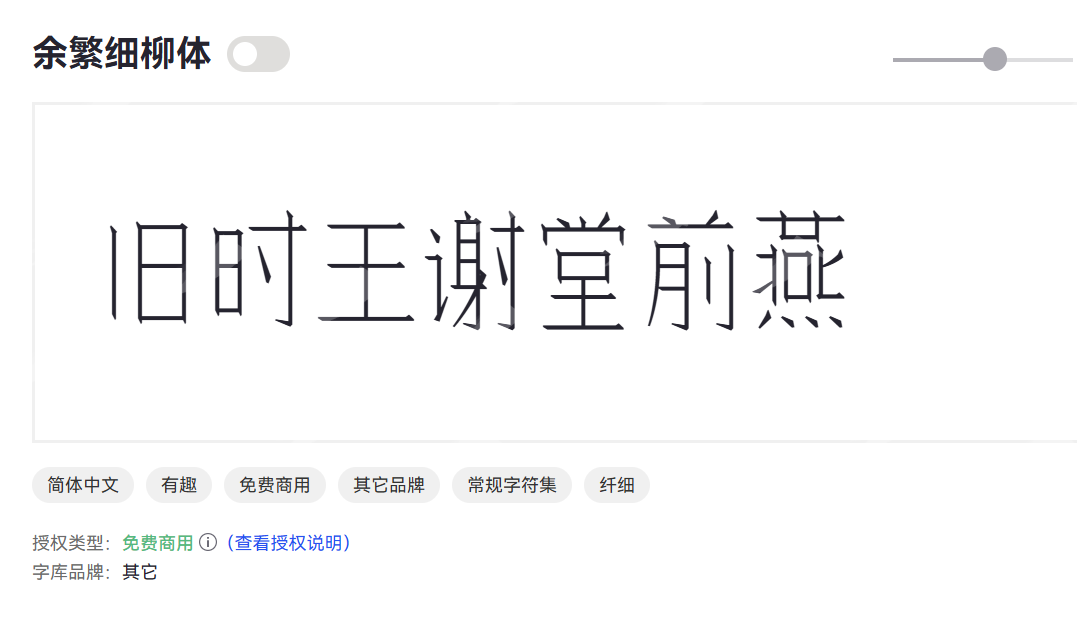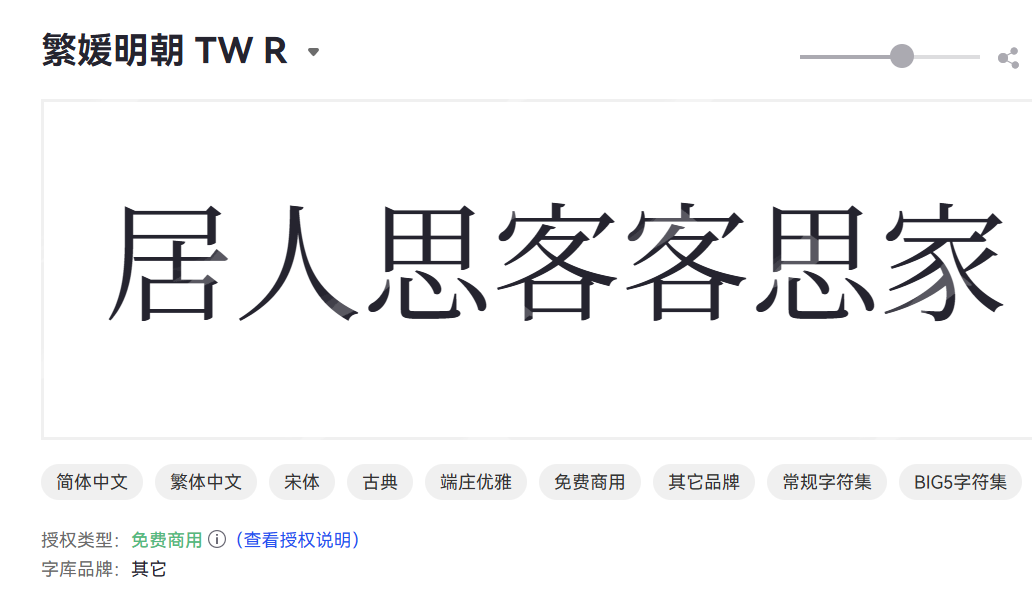
繁体字体可以商用吗?6 款可以免费商用的繁体字体
繁体字体是用来呈现繁体中文的字形集合,与我们常用的简体中文相对,繁体中文保留了汉字最原始、最复杂的笔画结构和字形。
每一个繁体字都像一幅微型的画作,笔画之间相互交织,结构严谨,充满着美学上的平衡感。例如,“龍”字比“龙”字多了许多笔画,但正是这些看似繁复的笔画,构筑了它独特的视觉张力。本文重点给大家分享 7 款可以免费商用的繁体字体。
本文就重点给大家介绍 6 款可以免费商用的繁体字体。
6 款可以免费商用的繁体字体
余繁丹青宋
余繁丹青宋是一款将传统宋体和国风的写意结合的繁体字体。它汲取了中国传统丹青水墨画的精髓,在宋体的骨架上融入了自然流畅、富有韵律感的笔墨细节。
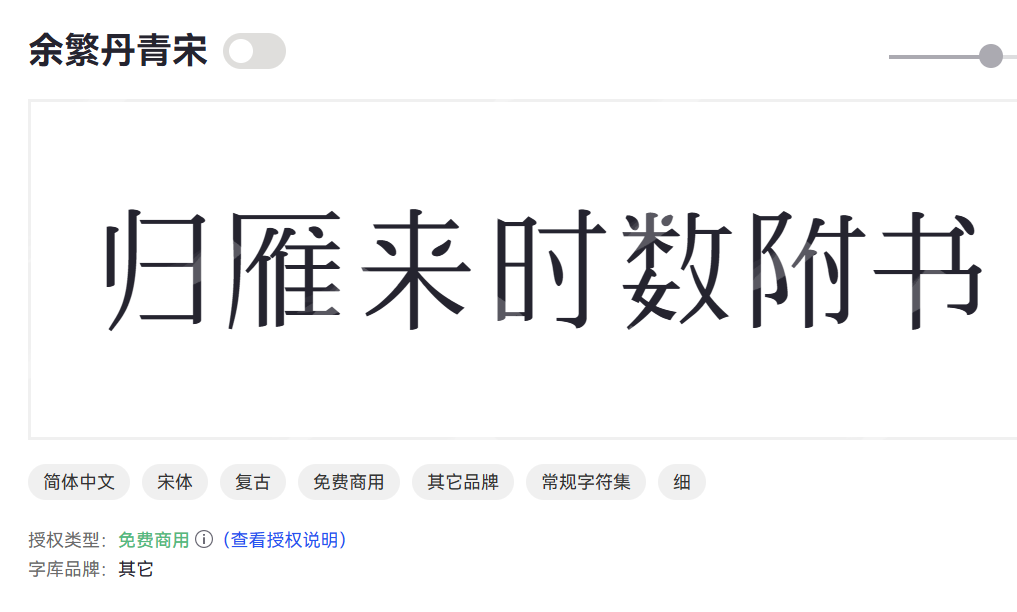
- 继承了宋体横细竖粗、结构严谨的特点,整体风格端庄大气。
- 浓厚的东方美学和传统文化气息。
- 笔画之间的衔接和转折自然流畅,富有节奏感。
- 适用于高端文化产品、艺术展览、国潮品牌、茶道、中式餐饮、文创设计等场景。
余繁细柳体
余繁细柳体是一款以柳条的纤细、柔美、飘逸为设计灵感的艺术字体。
- 整体字形舒展,富有动态美,不拘泥于传统字体的刻板。
- 透露细腻与优雅气质。
- 清新、淡雅、富有诗情画意的氛围。
- 适用于女性品牌与浪漫主题,我记得在一个三八节的海报就用的这款字体、
繁媛明朝
繁媛明朝保留明朝体横细竖粗、字形端正的古典韵味之余,融入了更为精致和女性化的细节,使得字体更加典雅、秀丽。
- 继承了明朝体横细竖粗、笔画棱角分明的经典特征。
- 笔画处理更为考究,细节丰富,展现出雅致的美感。
- 在古典中融入柔和元素,使其更具亲和力。
- 适用于高端文化品牌、复古风格设计、艺术品宣传、国风产品包装、书籍装帧、传统节庆活动等场景。
Aa可爱繁体字
Aa可爱繁体字是一款专为追求萌趣与个性的设计师打造的繁体中文字体。它将繁体字的传统结构与现代的可爱风格相融合,笔画圆润、饱满,字形活泼生动,充满了童真和亲和力,是传递轻松愉快设计场景的不错的选择。
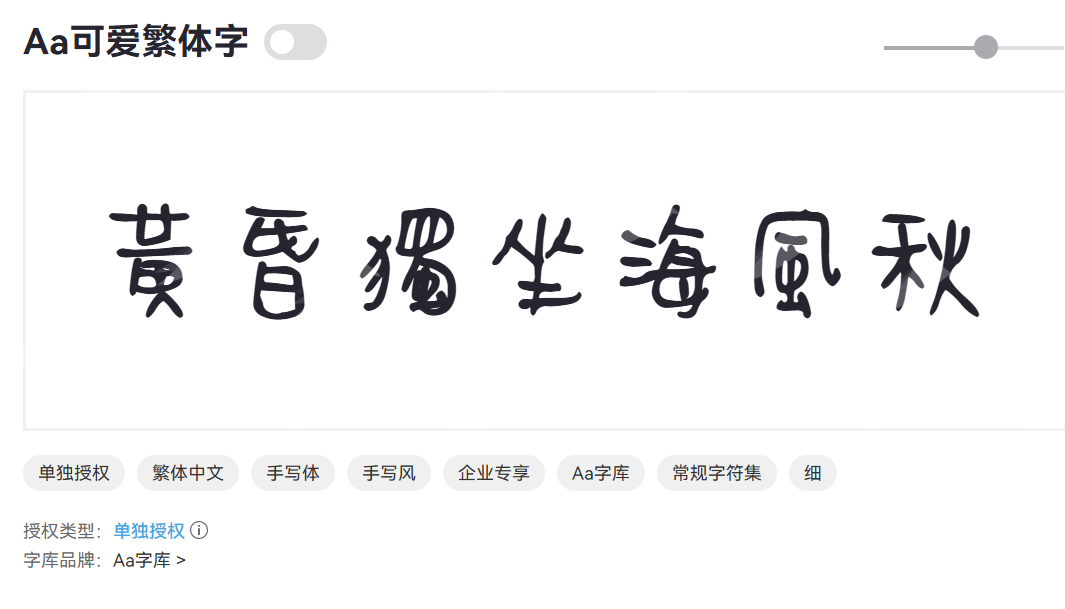
- 笔画圆润,造型Q萌,充满童趣和治愈感。
- 保留了繁体字的笔画和结构特点,便于港台及海外华人用户识别。
- 尽管可爱,但字形依然清晰,不影响阅读。
- 适用于萌系与儿童主题。
京華老宋体
京華老宋体是一款复古宋体字。它不同于现代标准化的宋体,字形稳重而富有故事感,如同老照片般引人追忆。
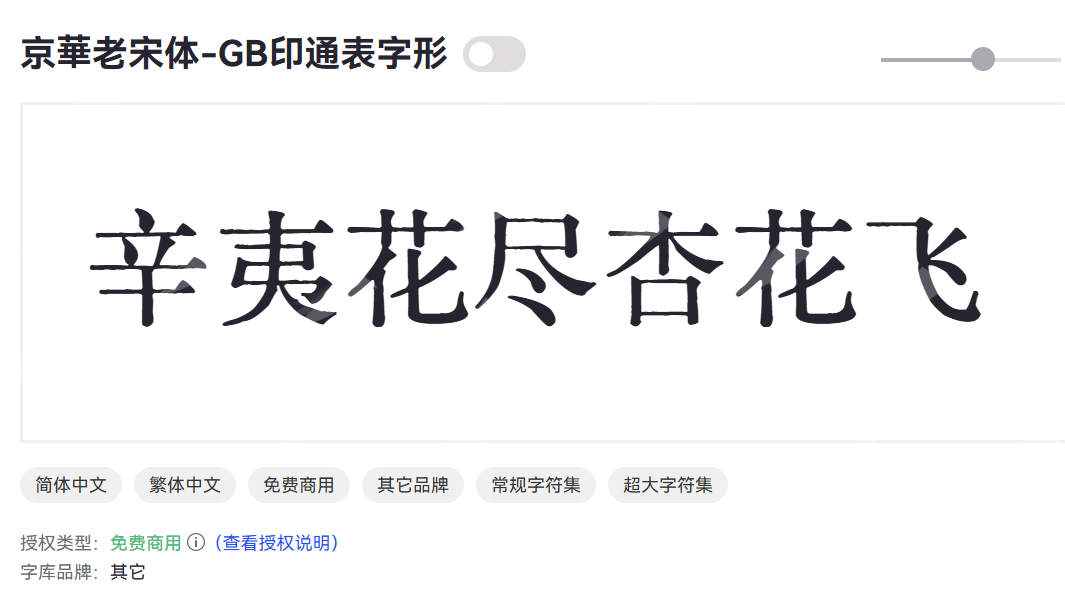
- 笔画细节保留了传统铅字印刷的痕迹,带有年代感。
- 整体风格沉稳厚重,结构方正,重心平稳,给人以信任和可靠感。
- 适用于历史文献、复古电影海报、文化遗产宣传、博物馆展览、传统品牌包装等场景。
黑糖糕体
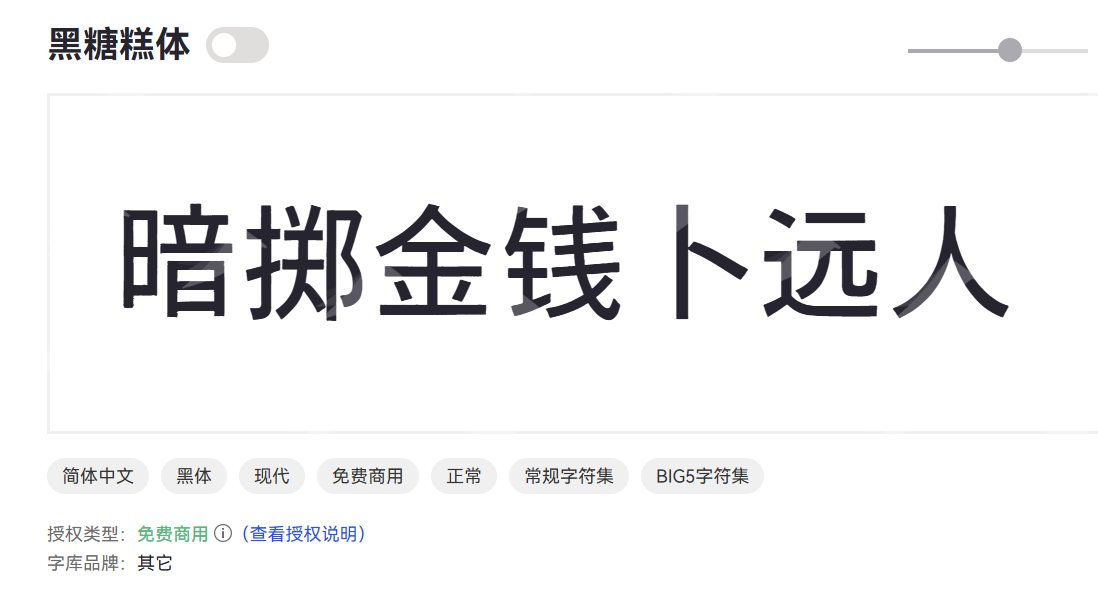
- 笔画圆润饱满,字形Q弹,充满甜点般的诱惑力。
- 整体风格轻松愉悦,给人带来温暖和放松的感觉。
- 适合表达幸福、甜蜜、放松的场景,如节日贺卡、社交媒体配图。